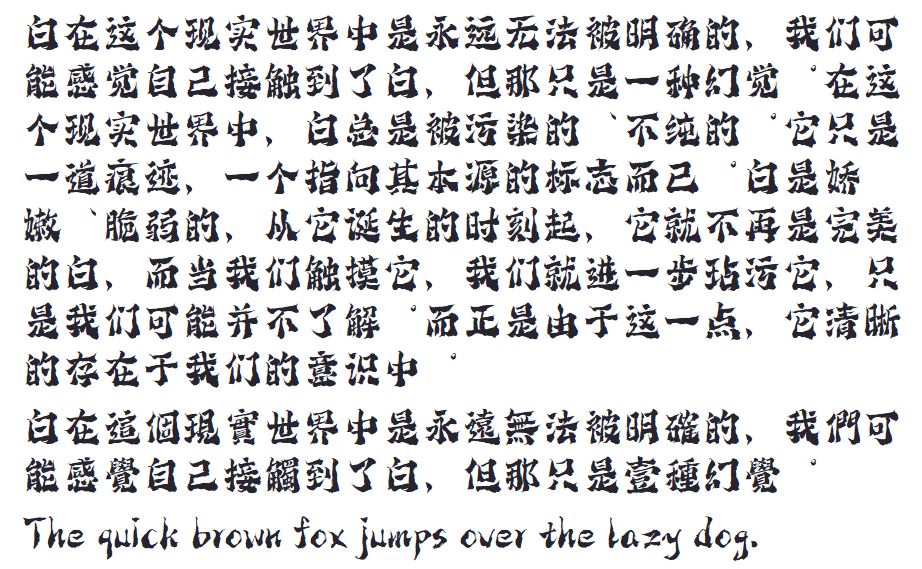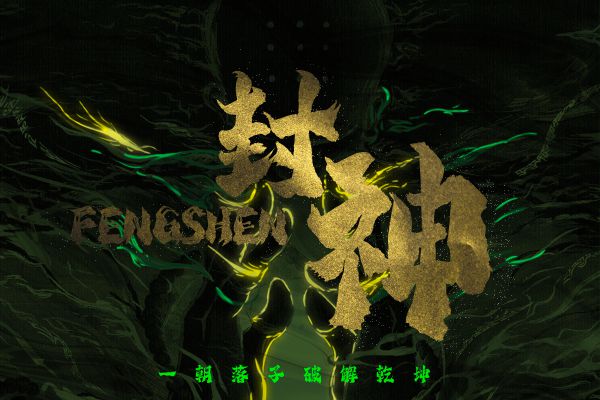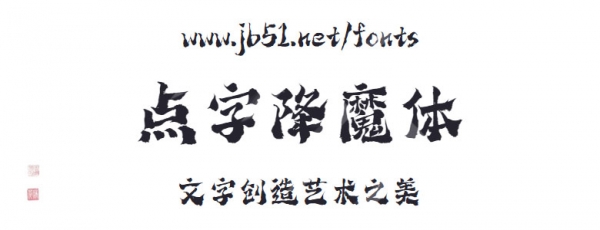
點(diǎn)字降魔體,字體加強(qiáng)線條形狀的雜亂無(wú)章,結(jié)構(gòu)上又井然有序,在靜和動(dòng),自由和嚴(yán)謹(jǐn)中無(wú)限平衡,給人一種向上生長(zhǎng)的積極態(tài)度,和向下扎根的堅(jiān)定不移。
字符集 GB2312+拉丁字符